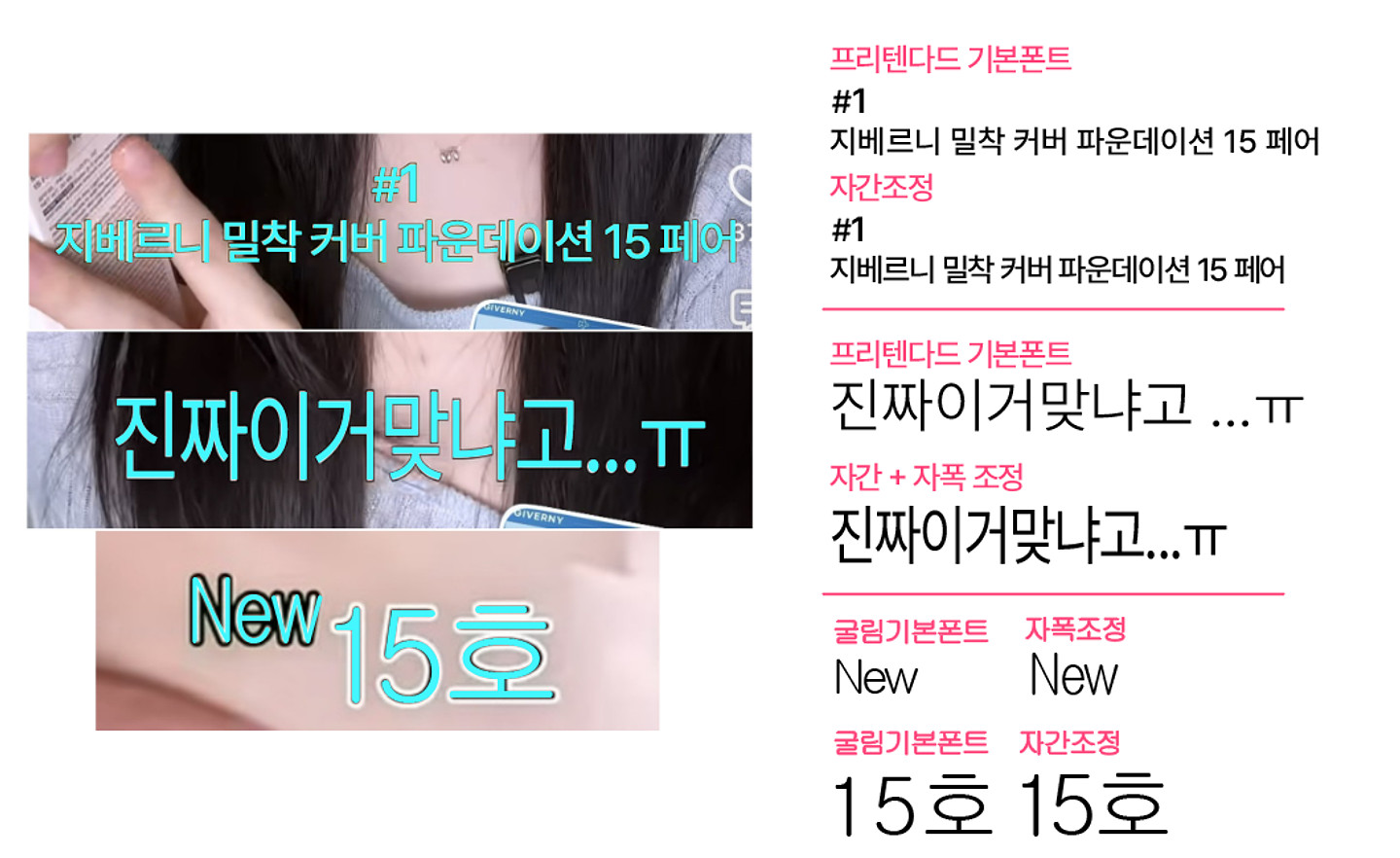
이 3가지 폰트(‘지베르니~’, ‘진짜이거~’, ‘New(영문폰트)’)에 대해 아시는 분 계실까요? 미리 감사드립니다!!
#1 지베르니 밀착커버 파운데이션 15페어 - 프리텐다드, 기본폰트에서 자간조정했습니다! 진짜 이거 맞냐고...ㅠ - 프리텐다드, 기본폰트에서 자간+자폭(글자 세로폭) 조정했습니다! New - 윈도우 기본폰트 굴림, 기본픈트에서 자폭(글자 세로폭) 조정했습니다! 15호 - 윈도우 기본폰트 굴림, 기본폰트에서 자간 조정했습니다!